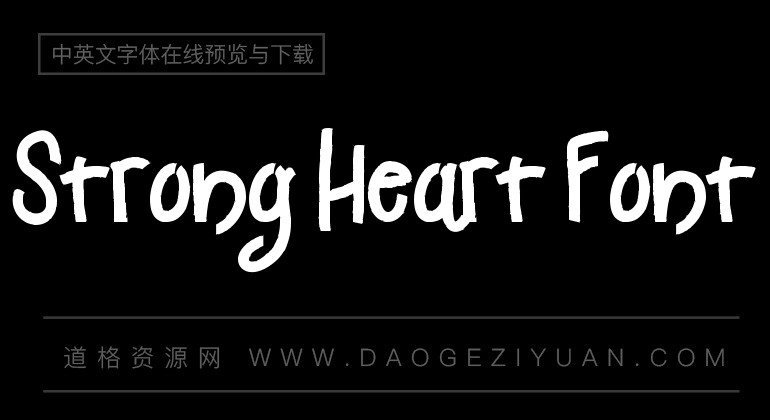
Strong Heart Font
Strong Heart 是一款现代风格的中文字体,由设计师 王嘉睿(Jiarui Wang)于2017年创建。其特点是粗壮的线条和刚毅的笔画,同时也具有一定的流畅性和优美感。 该字体的设计灵感来源于中国传统书法和现代设计的结合,强调了传统与现代的融合。这种设计风格使得 Strong Heart 字体既适用于传统的文化类设计,也适用于现代时尚、科技、商业等领域的设计。 Strong Heart 字体拥有多种字重和样式,包括常规、加粗、斜体等,可供不同的设计需求选择。同时,该字体还支持多种语言,包括中文、英文、日文、韩文等,使得它成为一款全球通用的字体。 总之,Strong Heart 字体是一款个性鲜明、设计独特的中文字体,适用于各种不同的设计场景。
Strong Heart Font是一款非常不错的手写艺术字体,具有很好的视觉感,适合于文化类的宣传设计、商业类品牌的广告和产品包装设计以及个性化文字排版等较多场景。